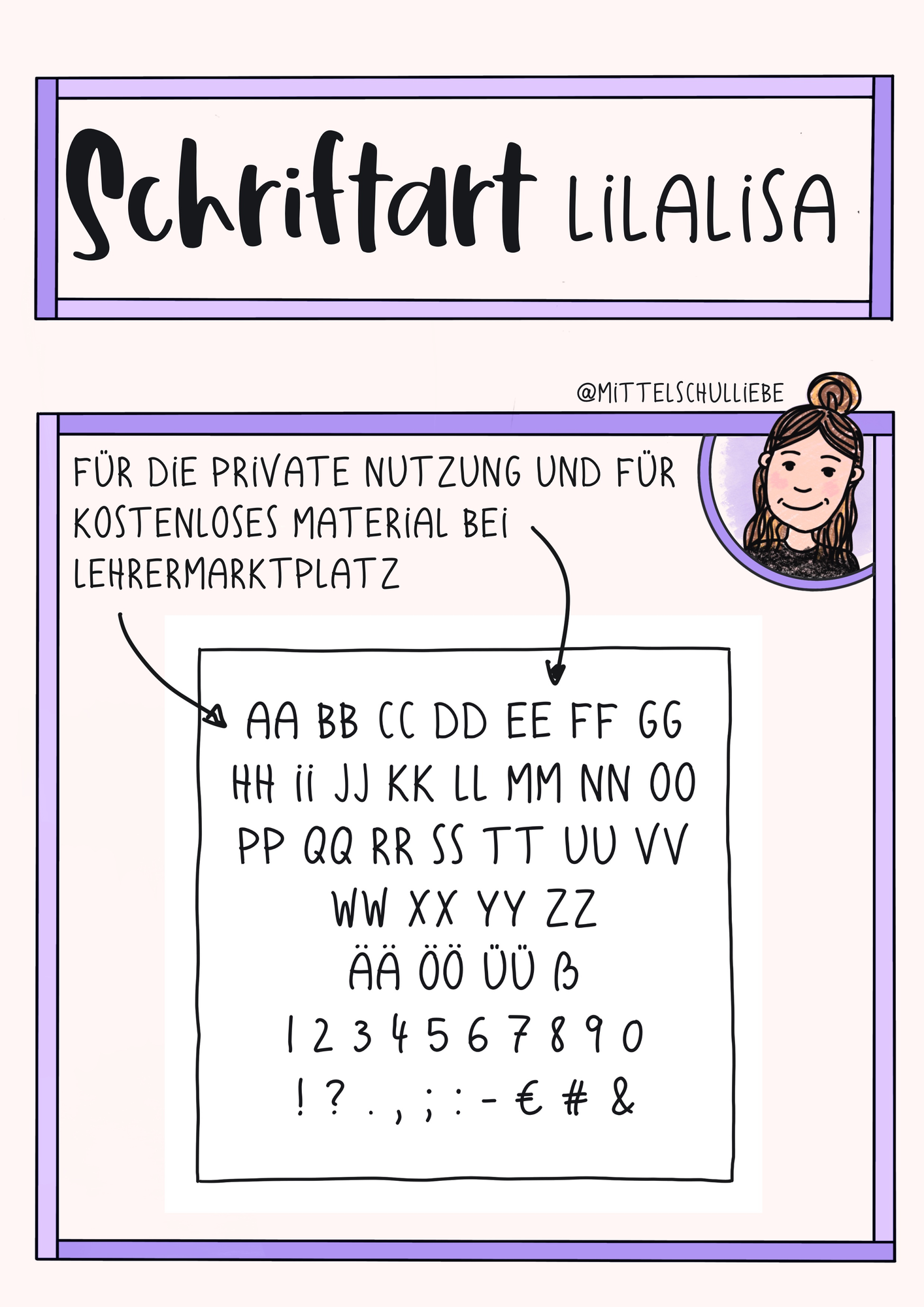
selbst erstellte Schriftarten - Schriftart „LilaLisa“ - Mittelschulliebe - Deckblatt
Selbsterstellte Schriftart für Arbeitsblätter und zur Verwendung für Unterrichtsmaterialien.
Schriftart „LilaLisa“
Eine tolle Schriftart!